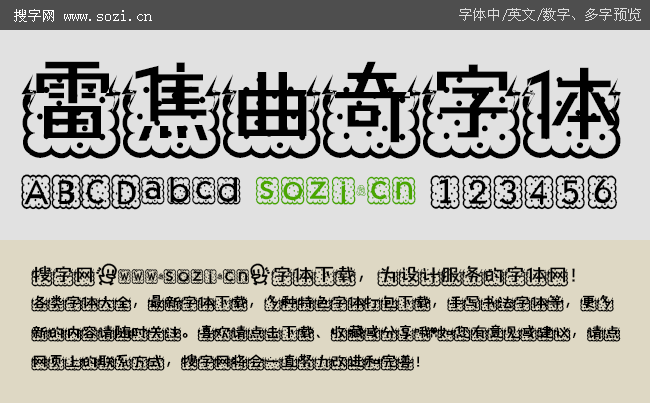
雷焦曲奇字體
搜字網(wǎng)給大家提供一款很卡通的手機(jī)中文字體下載。修改者給這款字體叫雷焦曲奇字體,這款手機(jī)中文字體以POP字體為原形,為字體標(biāo)點(diǎn)和英文加上了可愛(ài)的卡通餅干圖形外框,真的是非常有趣又可愛(ài)的一款字體,非常適合喜歡卡通的朋友在手機(jī)上安裝使用。